100 Etiquetas de Vino con mucho gusto tipográfico
Esta idea me pareció muy interesante para crear una entrada con diseños de envases de vino donde la tipografía tuviera un trato especial y os resulten interesantes de observar y analizar.
Es una recopilación muy extensa pero también muy cuidada, he escogido uno a uno cada uno de los ejemplos, los hay muy ornamentados o caligráficos, pero también muy minimalistas y limpios donde la aplicación tipografía ha sido utilizada con multitud de técnicas diferentes, bajos relieves, cuños, en goma elásticas, sobre madera, corcho....
Aquí os dejo las 100 etiquetas, seguro que saboreáis cada una de ellas:
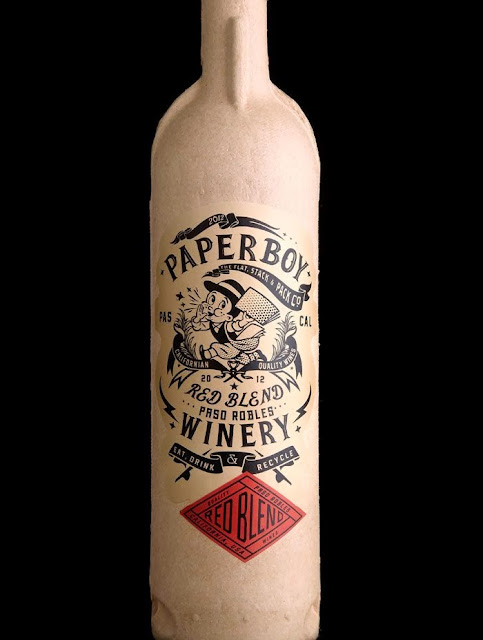
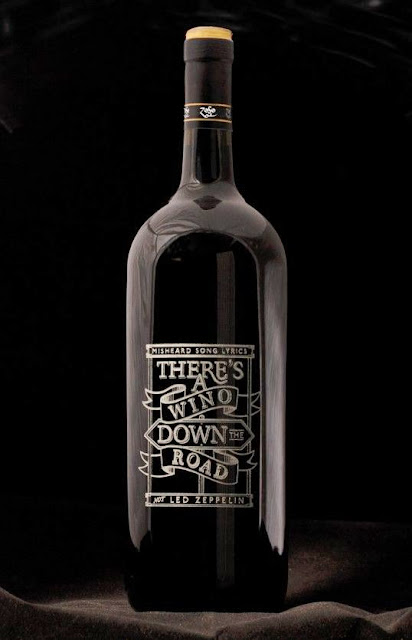
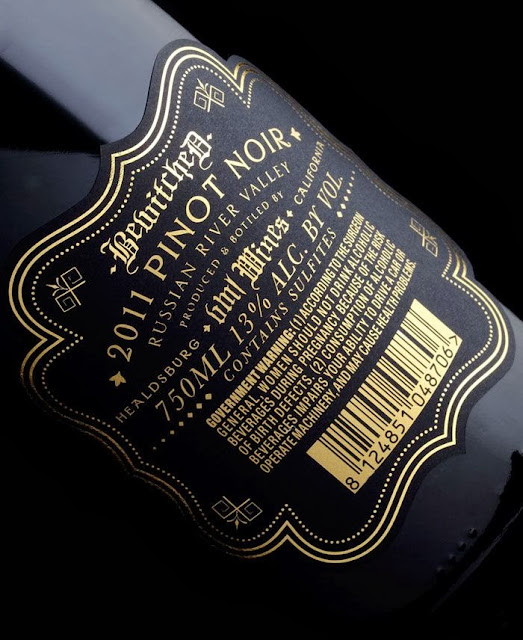
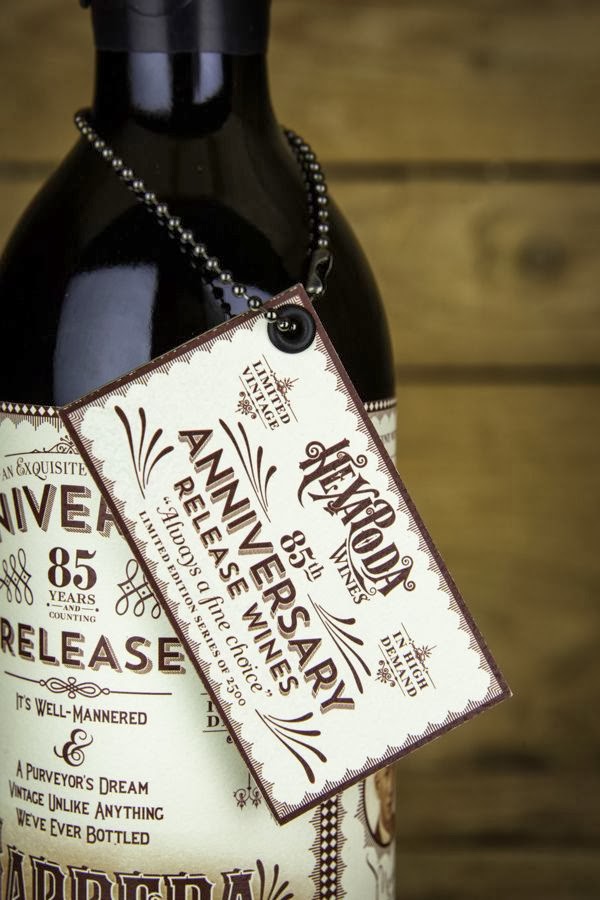
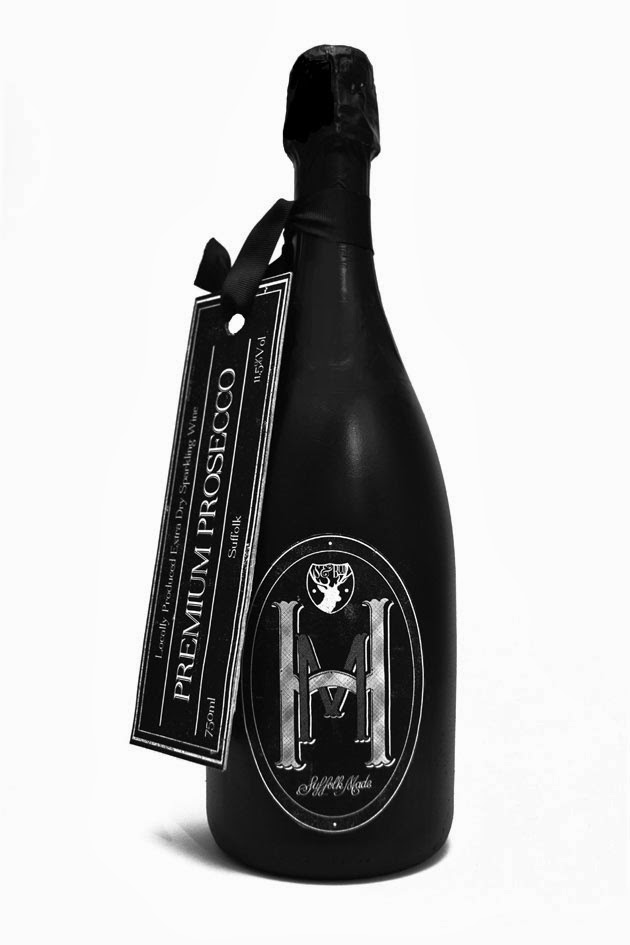
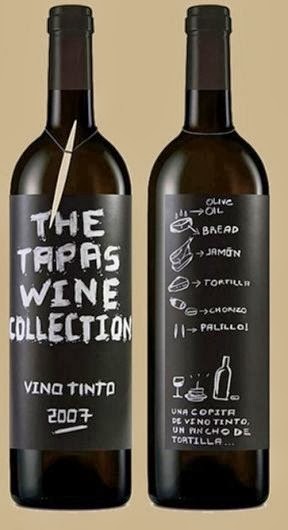
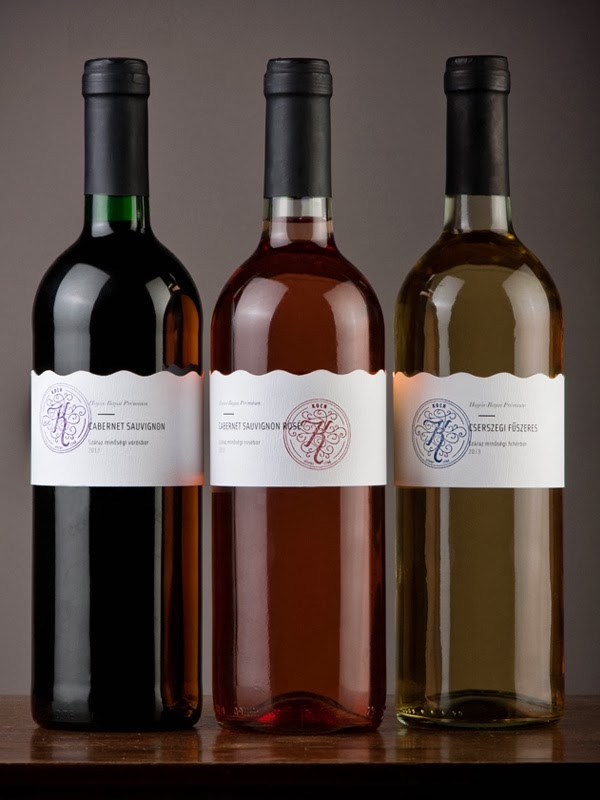
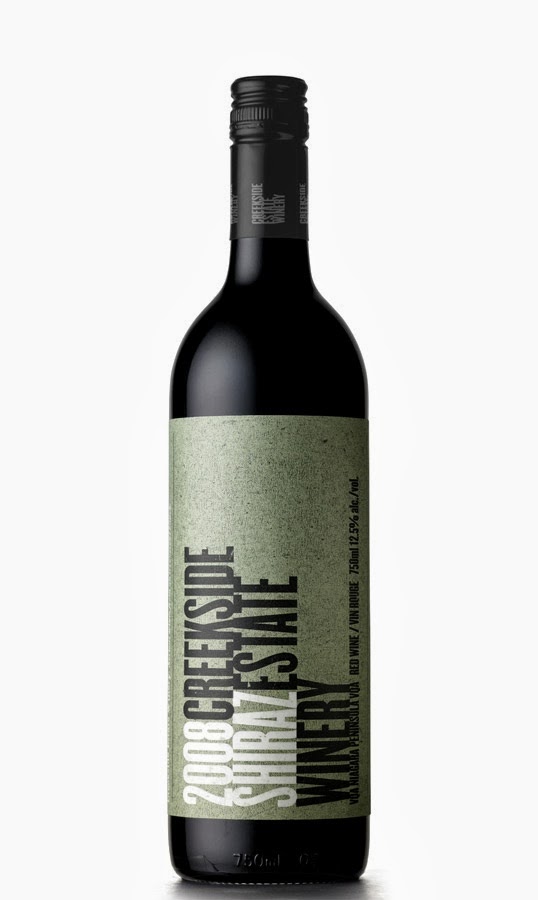
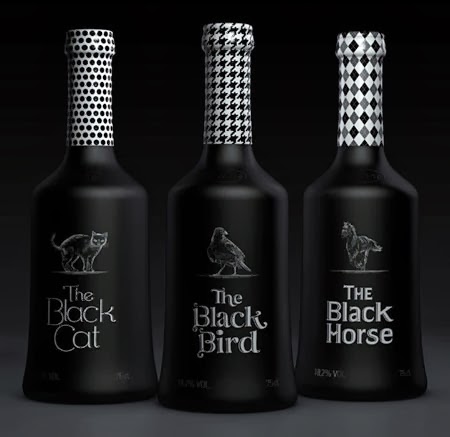
Creo que se ha colado un aceite de oliva